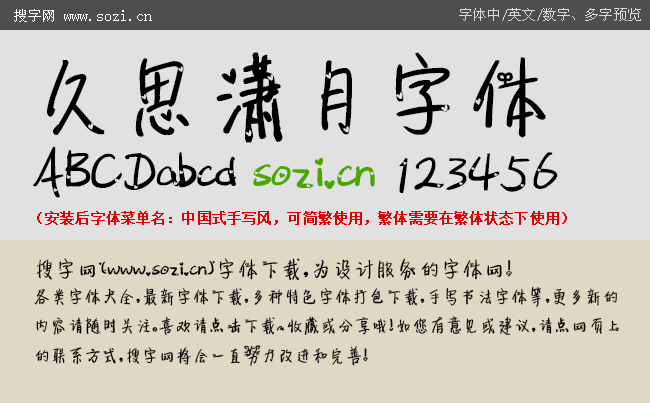
久思瀟月字體
搜字網(wǎng)給大家提供一款書(shū)法風(fēng)格手機(jī)中文字體下載。修改者將它命名為久思瀟月字體,這款手機(jī)字體是是以新蒂下午茶書(shū)法字體為原形。筆畫(huà)間點(diǎn)綴了一些卡通花紋,新蒂下午茶字體是一款清新淡雅的手寫(xiě)體,點(diǎn)綴了花紋后增添了趣味性,又有手寫(xiě)字體的藝術(shù)性,特別適合喜歡手機(jī)字體個(gè)性一些的朋友在手機(jī)上安裝使用。